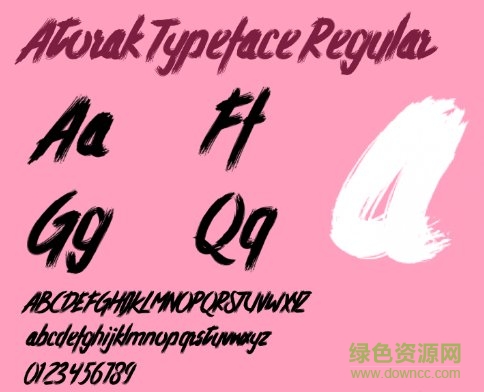
typeface字體是一款傾斜飄逸的英文字體,整體結(jié)構(gòu)十分悅目,讓人頓覺(jué)精致書(shū)寫(xiě)的干凈體驗(yàn),喜歡的朋友就來(lái)綠色資源網(wǎng)下載體驗(yàn)吧!
Atorak Typeface字體家族系列主要提供Regular等字體風(fēng)格樣式,字庫(kù)完整,字符分布范圍較廣,能滿(mǎn)足廣大設(shè)計(jì)師們的平面設(shè)計(jì)、包裝設(shè)計(jì)等需要。